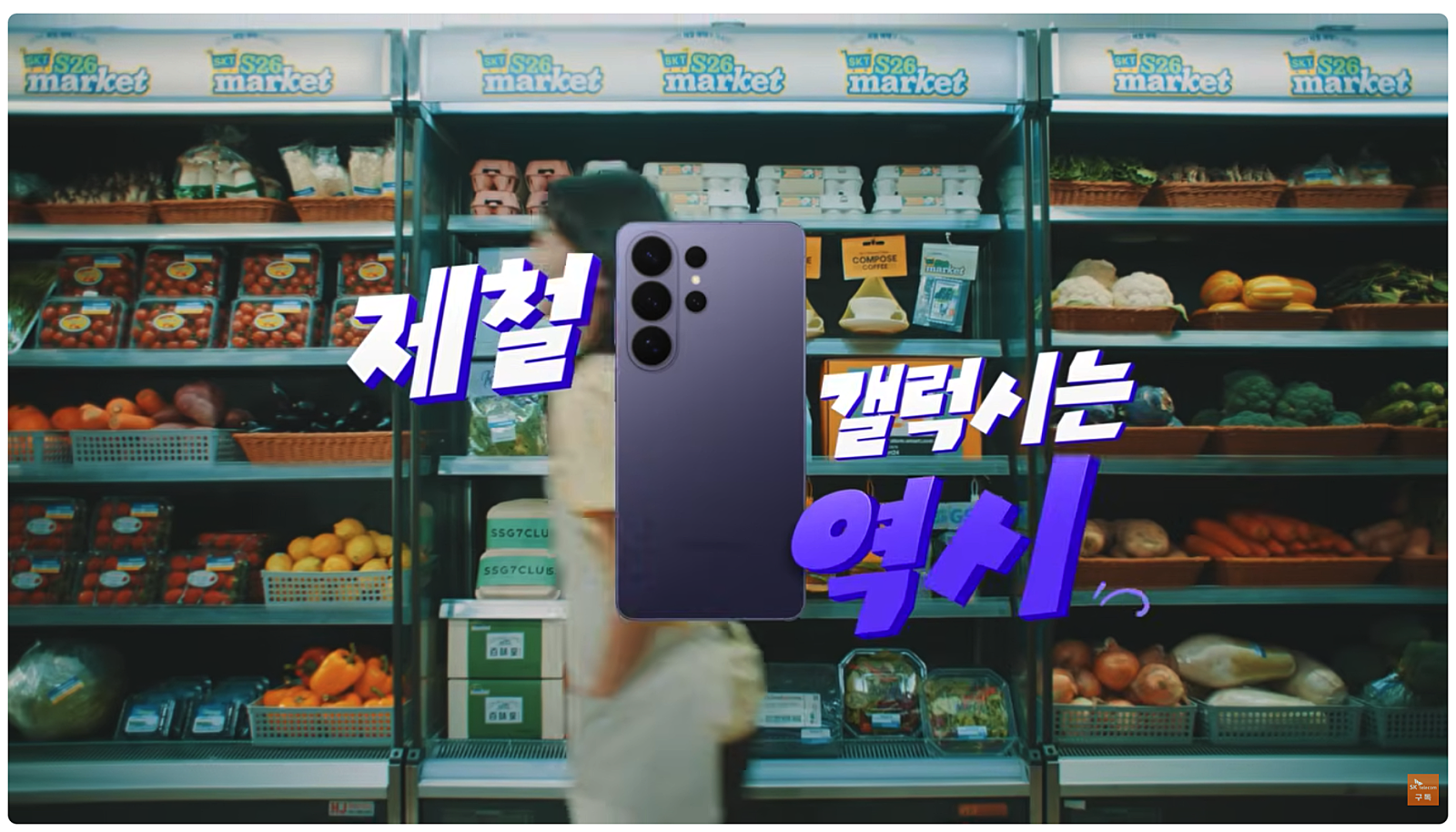
와일드각 — 김씨폰트공방에서 배포하는 무료 폰트입니다. 정형화된 자소에서 벗어난 굵고 비틀린 획으로 거칠고 역동적인 인상을 만드는 장식체
이름이 형태를 그대로 말해 줍니다. 와일드와 각을 붙인 이름대로, 한글 활자의 틀을 벗어난 인상적인 획이 특징입니다. 굵은 획과 기울어진 구조가 속도감을 만들어 역동적인 인상을 냅니다. 파일에서 재어 보면 낱자가 가로로 넓게 퍼져 있어 짧은 문구를 크게 세울 때 시원합니다.
현대 한글 11,172자를 모두 담아 어떤 글자를 넣어도 빠지지 않습니다. 포스터나 스포츠, 액션 계열의 헤드라인에 어울리고 본문에는 전혀 맞지 않습니다. 인쇄와 웹, 포장지, 영상, 임베딩, BI와 CI까지 허용되지만 배포된 형태 그대로 써야 하고 수정과 편집은 금지됩니다.